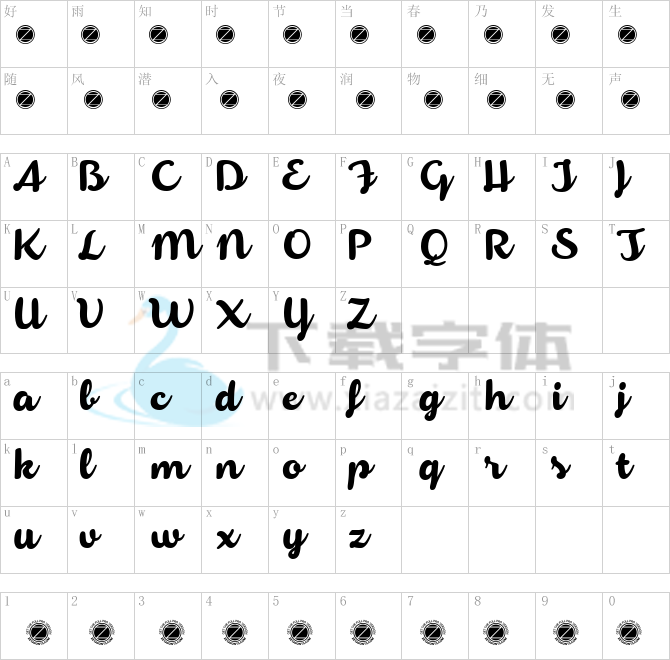
Armonioso.otf字体下载,这款字体结构工整、笔画清晰,兼顾美观与易读性,适用于标题、正文、海报、包装、LOGO 等多种场景。字形优雅稳定,风格百搭耐看,适配日常排版与创意设计,让文字呈现更舒适、更具质感。Armonioso.otf字体下载一笔一画,皆是细节,以均衡的比例、流畅的线条打造舒适视觉体验,字形端正大气,风格简约现代。无论是商业设计、品牌宣传还是日常排版,都能轻松驾驭,让文字更有格调与力量。Armonioso.otf字体下载字体下载。